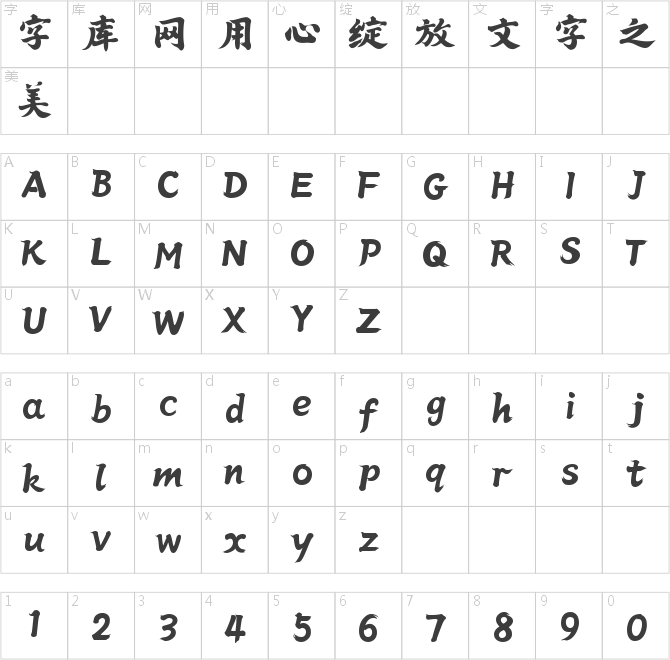
字體名稱: 潮字社空海心經
潮字社空海心經簡繁
字形中正,露鋒起筆,運筆流暢,線條內部運動極為豐滿,并非平鋪直敘,在不斷變化的筆法當中呈現出唐代風韻。各筆畫粗細相對統一,進而展現出字體的相對厚度。點畫多變且飽滿豐腴,內部有著復雜的毛筆椎體運動感,使得點畫的層次更多,更有韻味。轉折處圓轉與方正并存,展現出單字的豐富多樣。